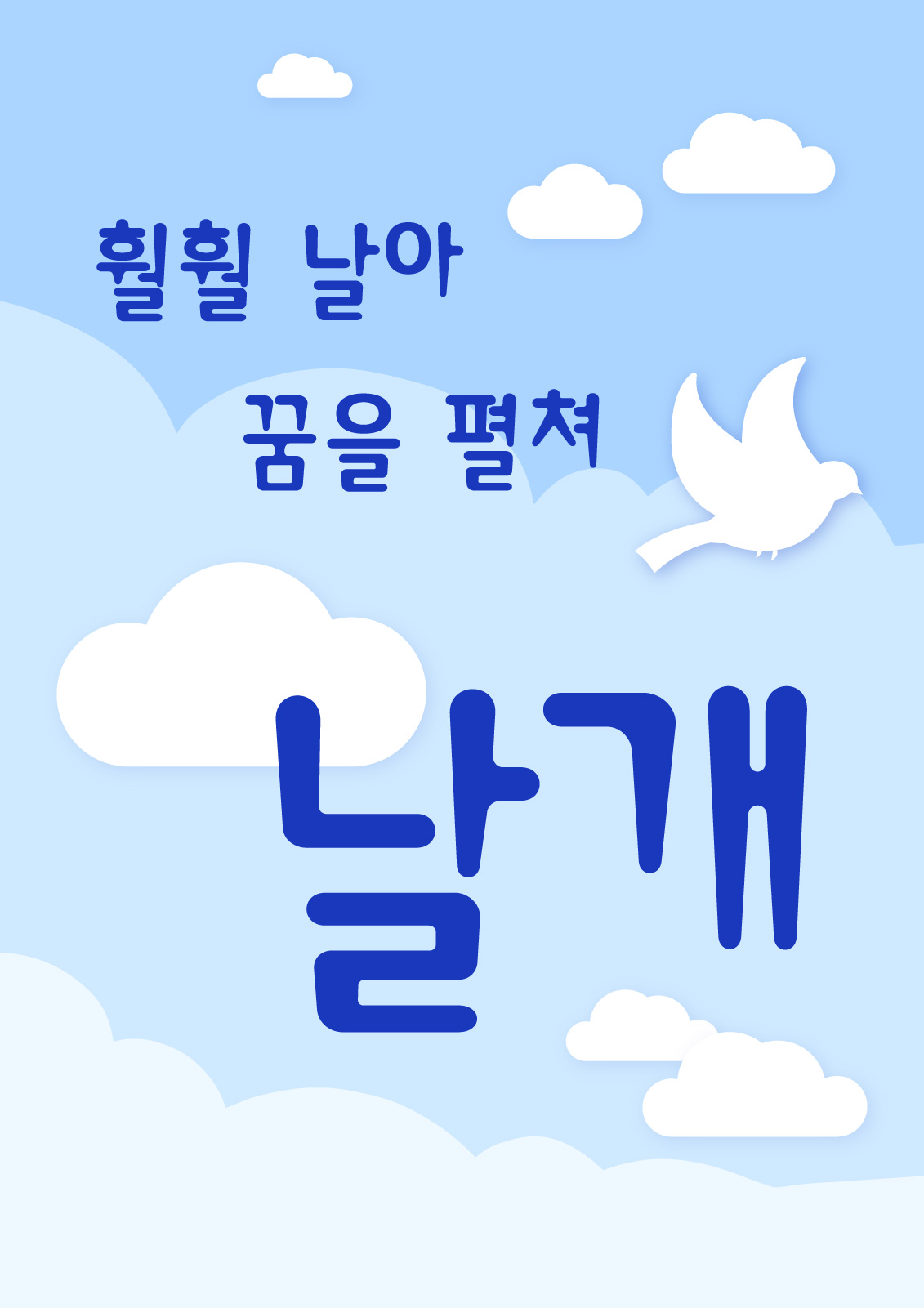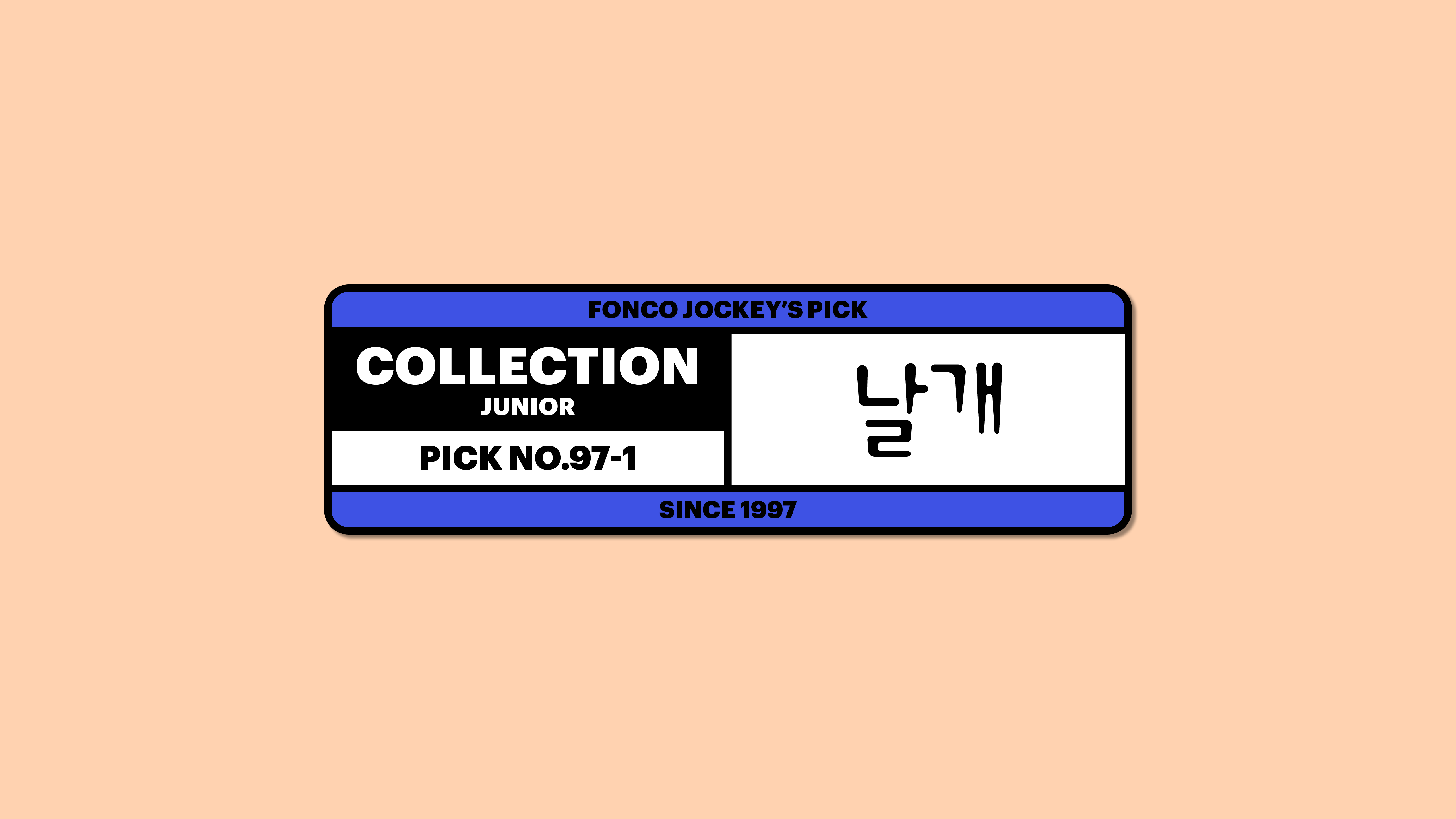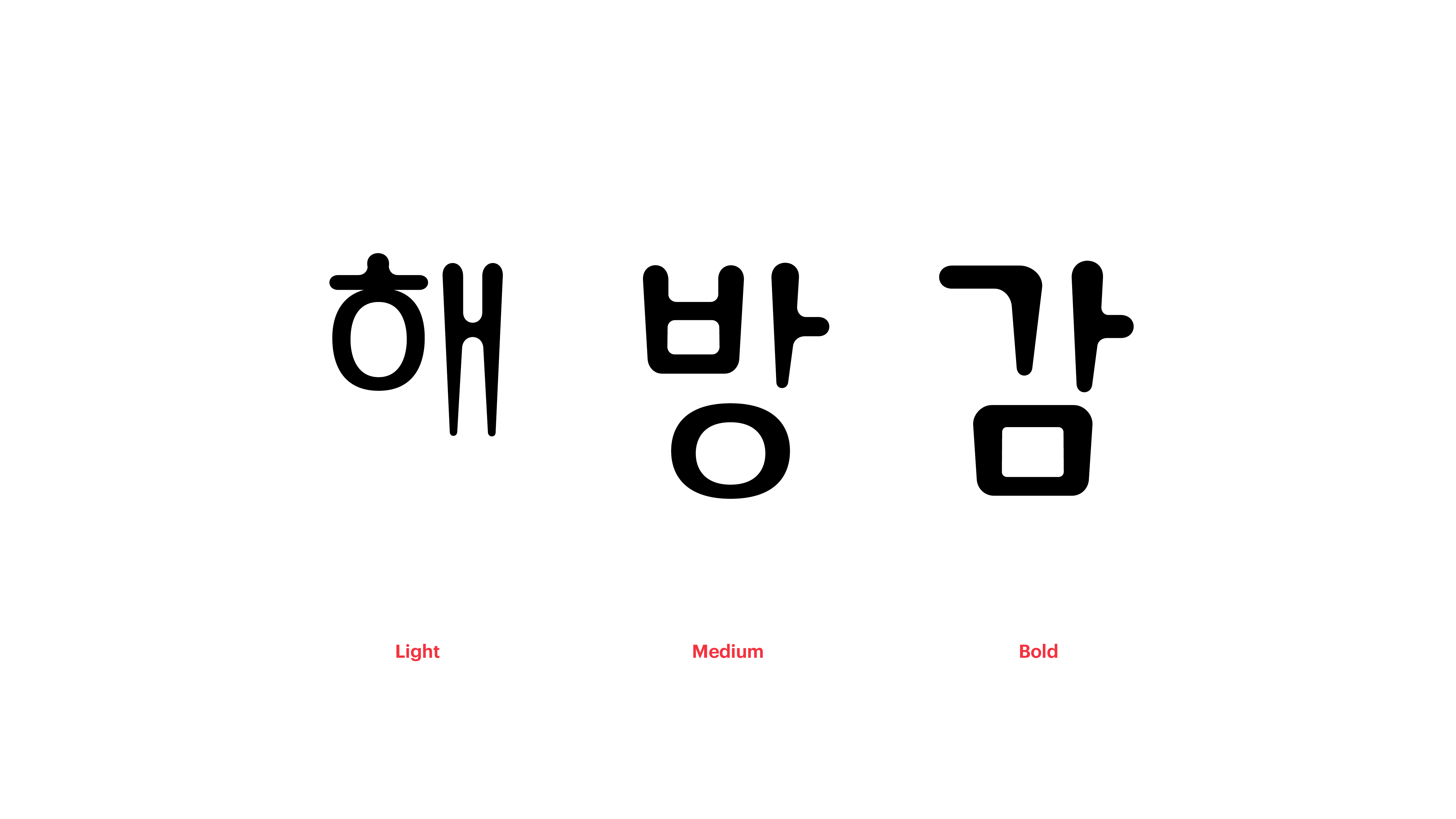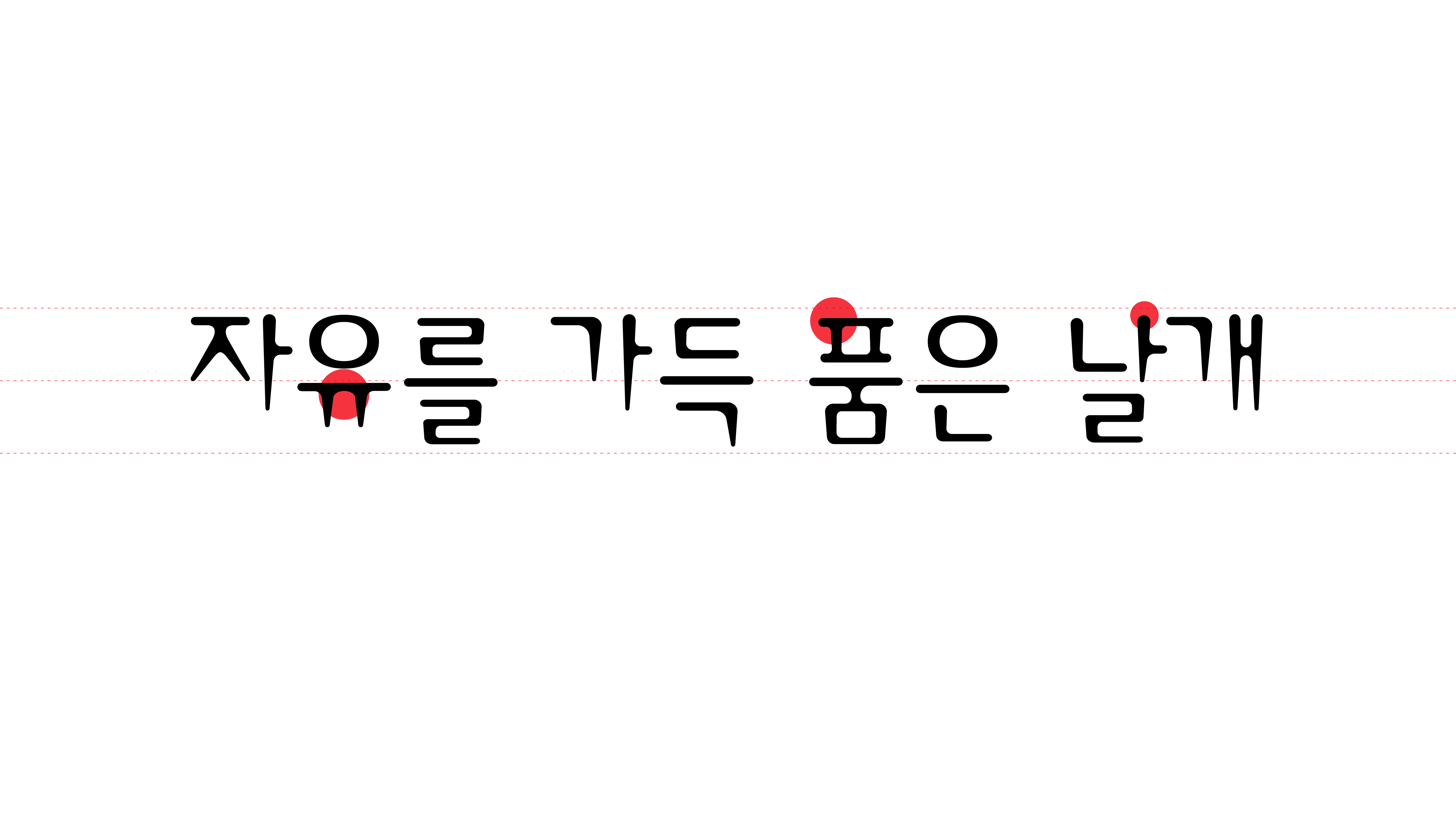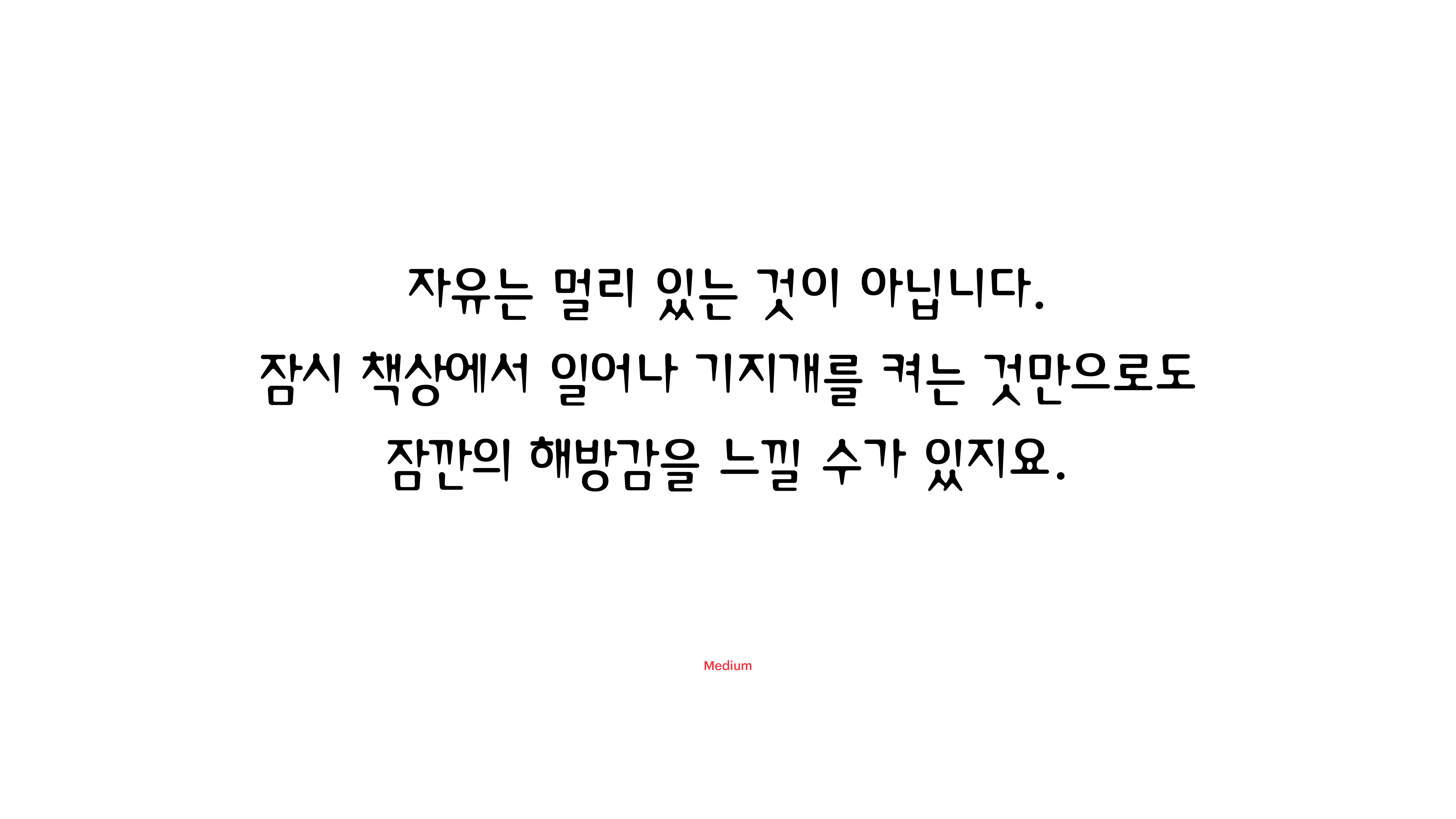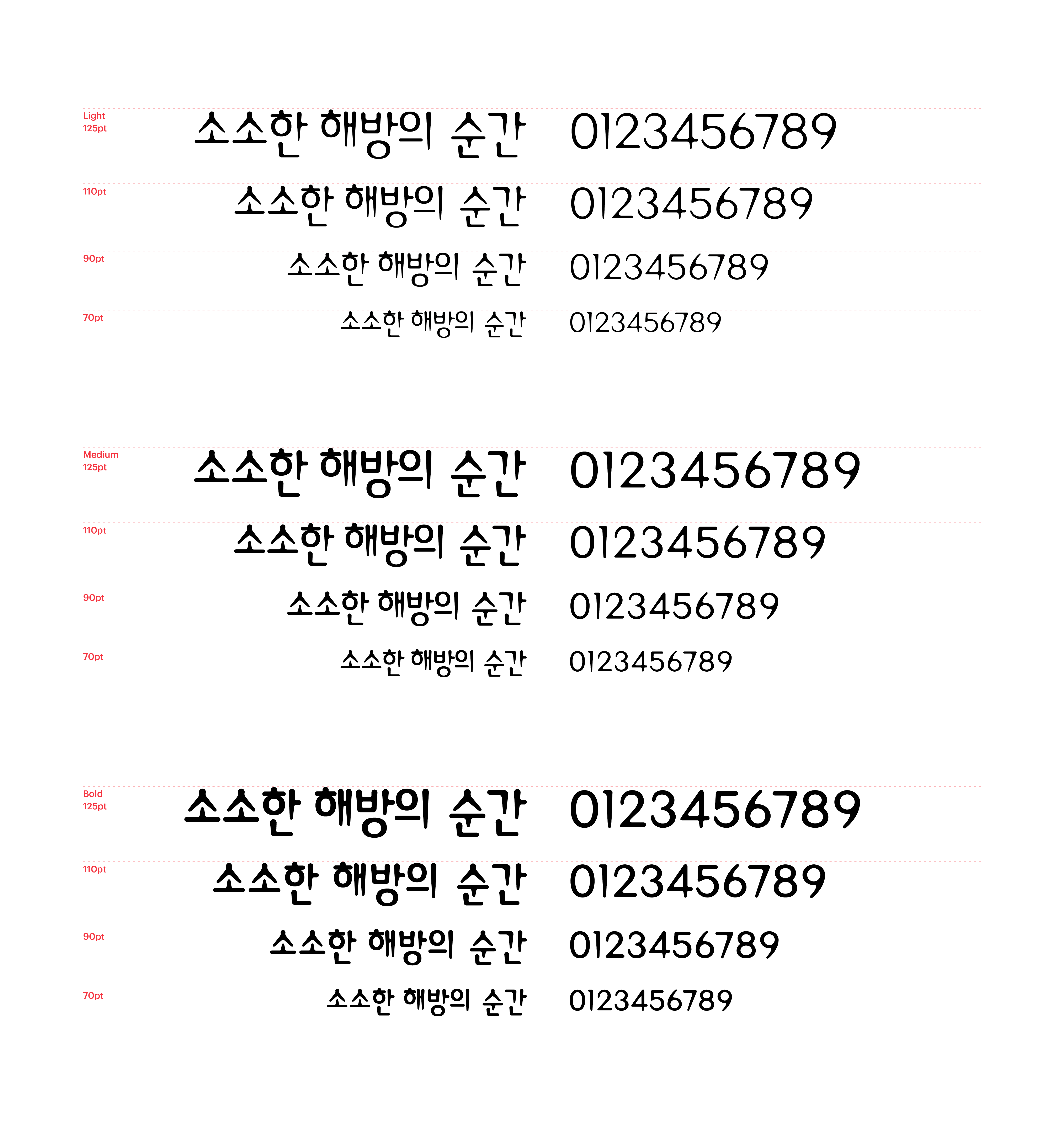
자유는 멀리 있는 것이 아닙니다. 잠시 책상에서 일어나 기지개를 켜는 것만으로도 잠깐의 해방감을 느낄 수가 있지요. 날개체는 그런 소소한 해방의 순간들을 담아낸 폰트입니다. 각 자음과 모음의 개별적 생김새를 고려하여 획의 굵기와 강약을 다양하게 표현해두었지요. 덕분에 각각의 글자가 살아서 춤을 추는 느낌. 자유를 가득 품은 날개체와 함께 나만의 자유를 창조해보세요.
Yoon 날개